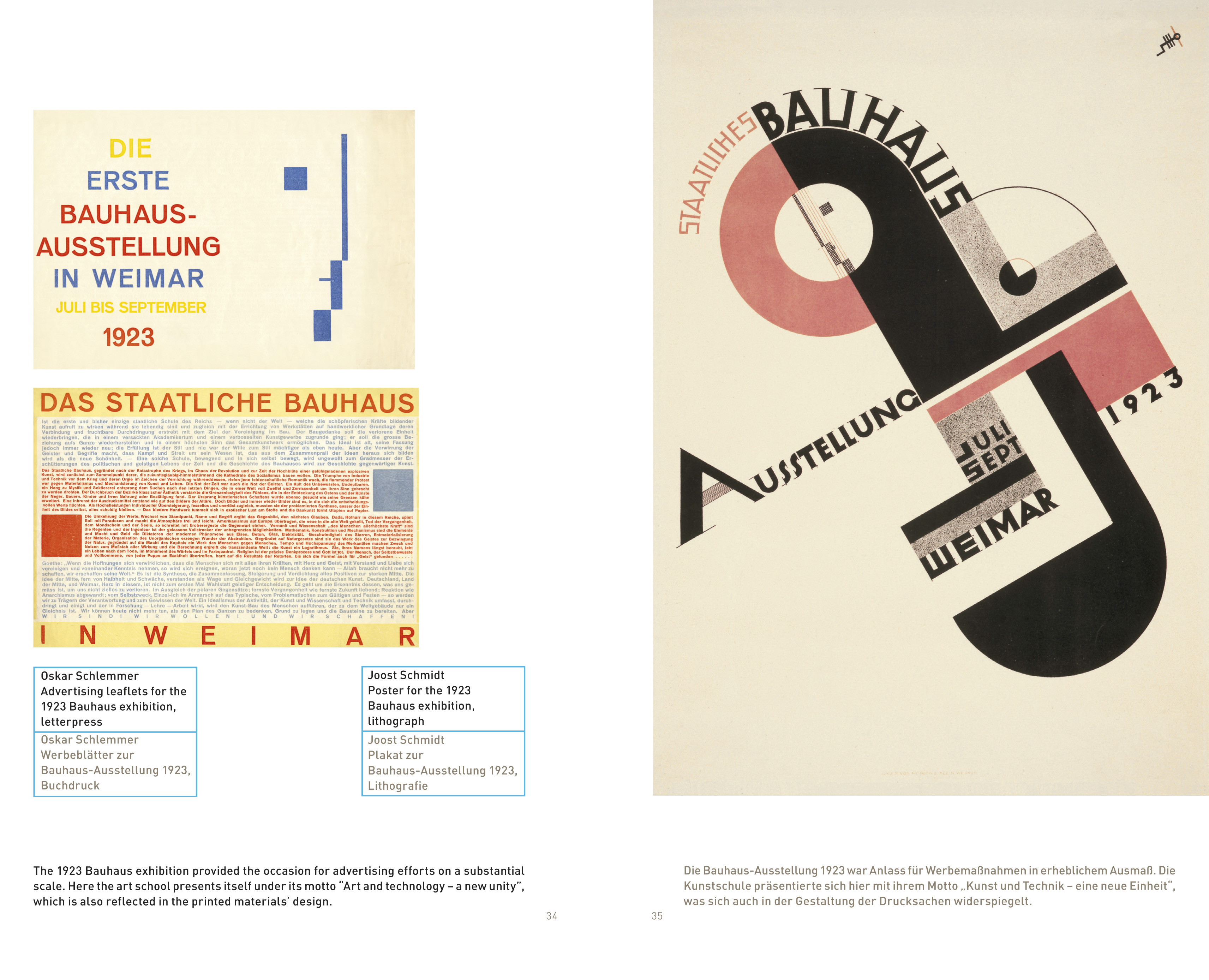
bauhaus.typography / bauhaus.typografie
100 Werke aus der Sammlung des Bauhaus-Archiv Berlin
Das Bauhaus-Archiv / Museum für Gestaltung in Berlin besitzt eine der umfangreichsten Sammlungen an typografischen Werken aus dem Bauhaus. Mit der hier gezeigten Auswahl möchten wir Einblicke in diesen reichen Bestand geben sowie die vielfältigen Möglichkeiten und den facettenreichen Umgang mit diesem Medium am Bauhaus verdeutlichen.
Das Bauhaus – die wohl bedeutendste Avantgardeschule des 20. Jahrhunderts, 1919 von dem Architekten Walter Gropius in Weimar gegründet, 1925 nach Dessau umgesiedelt und 1933 in Berlin unter dem Druck der Nationalsozialisten geschlossen – bietet zahlreiche Assoziations- und Anknüpfungspunkte für alle, die an Architektur und Gestaltung interessiert sind. In den Werkstätten des Bauhauses entstanden moderne Gegenstände für eine neue Lebenswelt, vom Alltagsobjekt bis zum Wohnhaus. Nicht wenige Entwürfe, vor allem aus den Bereichen Möbel und Architektur, erlangten historische Bedeutung.
Typografie spielte schon bei der Gründung des Bauhauses eine bedeutende Rolle. In den ersten Jahren noch von der expressiven-kalligrafischen Bildsprache eines Johannes Itten geprägt, trug das Bauhaus, insbesondere durch die Lehrer László Moholy-Nagy, Herbert Bayer und Joost Schmidt, zur Verbreitung der sogenannten Neuen Typografie bei. Vorwiegend in der Eigenwerbung für die Schule und ihre Produkte eingesetzt, aber auch zunehmend für Auftragsarbeiten zeichnen sich die Werke häufig durch einen klaren Satzspiegel, den Einsatz prägnanter typografischer Zeichen, starke Kontraste von Farbe, Größe und Position, normierte Formate sowie die Durchdringung von Bild und Schrift aus.